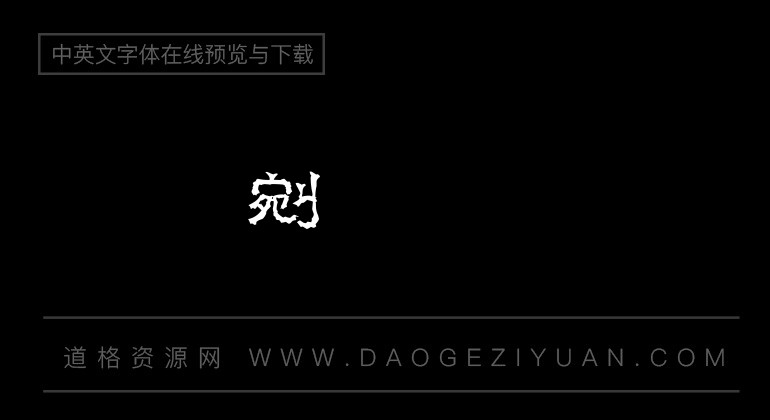
文鼎荆棘体
文鼎荆棘体是一种新兴的中文字体,它拥有清新、大气、稳重的设计风格。文鼎荆棘体具有较大的字符宽度,让字体显得更加饱满,更清晰,更有层次感,更有视觉冲击力。它的字形设计更加紧凑,节奏感更强,更适合用于大型文字的排版,也可以用于小型文字的排版。
文鼎荆棘体是一款非常不错的手写艺术字体,具有很好的视觉感,适合于文化类的宣传设计、商业类品牌的广告和产品包装设计以及个性化文字排版等较多场景。